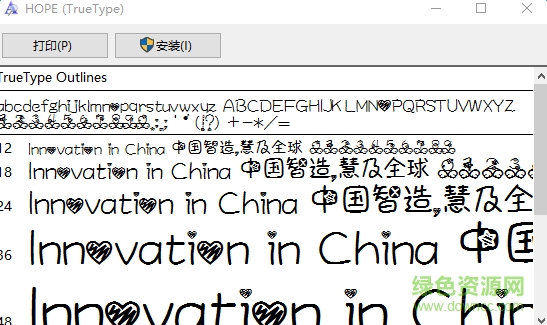
女神是美人字體是一款非常好看的電腦字體,這款字體與普通字體都不相同,它寫出來(lái)的字是很好看的,而且具有自己獨(dú)特的魅力,喜歡的鵬偶遇就來(lái)綠色資源網(wǎng)下載吧。
女神是美人字體是一款具有藝術(shù)風(fēng)格的字體,當(dāng)然寫出來(lái)的字也會(huì)很有特色,大家可以將這款字體用于很多方面,歡迎有需要的朋友來(lái)綠色資源網(wǎng)下載。